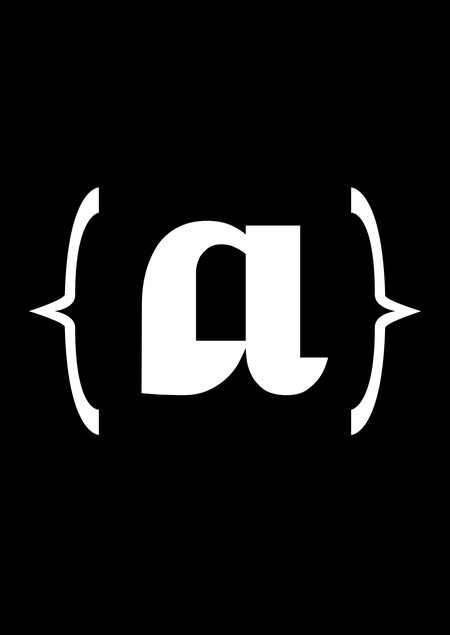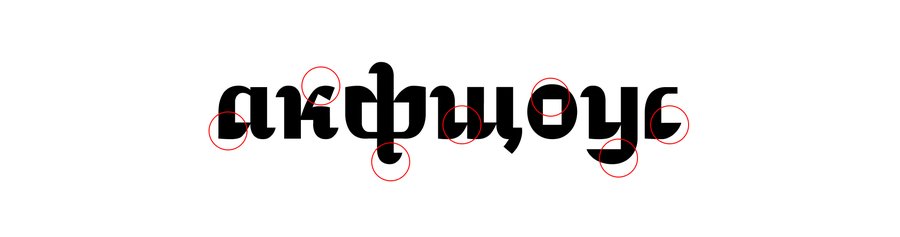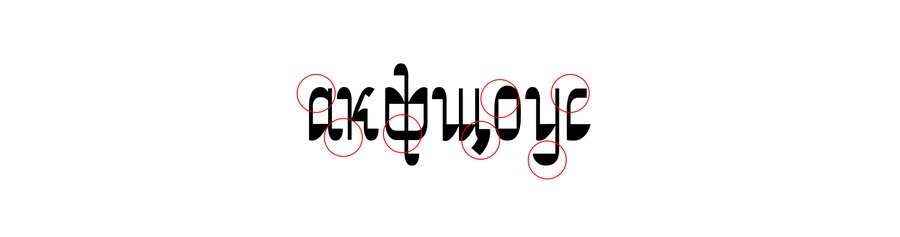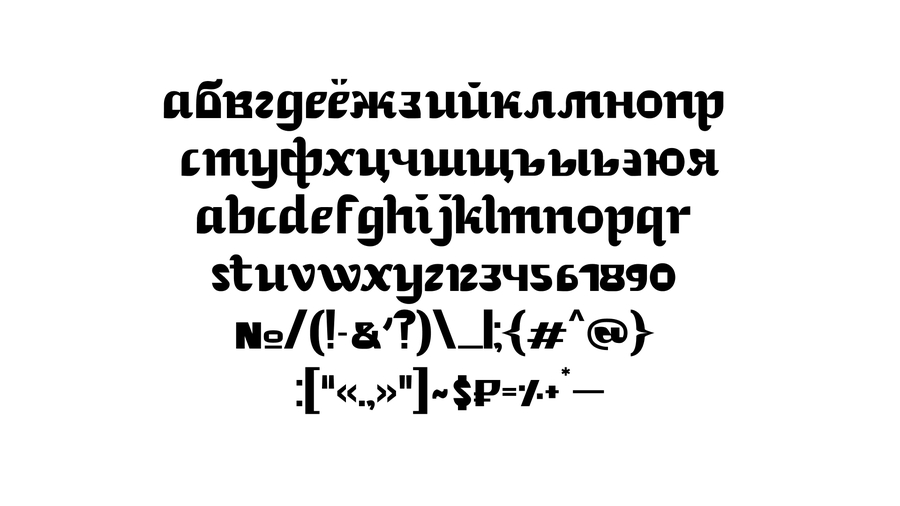
шрифт ambrazure
Шрифт вдохновленный написанием с наклоном пера и выполненный в двух начертаниях: обычном и узком (regular и narrow).
1. скошенные овалы и полуовалы 2. скошенные засечки 3. широкие вертикальные стемы
1. скошенные овалы и полуовалы 2. скошенные засечки 3. узкие вертикальные стемы